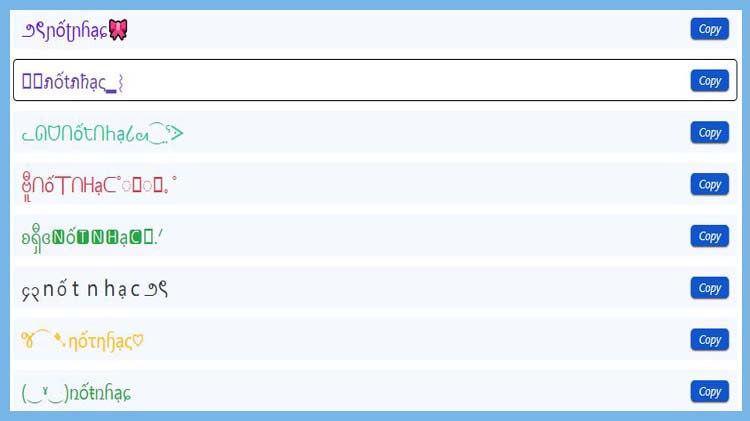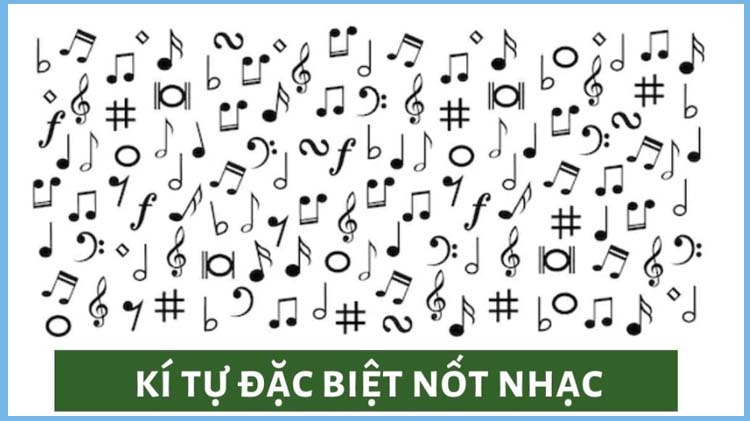
Tuyển tập các kí tự nốt nhạc đơn sắc, có màu sắc, chữ nghệ thuật 2025
Kí tự nốt nhạc hay kí tự âm nhạc là một trong những biểu tượng được sử dụng phổ biến trong những status trên facebook, instagram, tiktok hay được dùng để đặt tên người chơi trong các tựa game phổ biến như FF, Liên Quân, PUBG,... Những kí tự này không chỉ gây ấn tượng với người đọc mà còn thể hiện khả năng sáng tạo và niềm đam mê âm nhạc của người sử dụng.
Trong bài viết này của MobiFonts, các kí tự đặc biệt nốt nhạc được phân loại thành 3 nhóm chính là kí tự nốt nhạc đơn sắc, kí tự nốt nhạc có màu sắc và kí tự âm nhạc chữ nghệ thuật. Ngoài ra, chúng tôi cũng giải đáp những thắc mắc của người đọc về các kí tự đặc biệt âm nhạc này.
Kí tự nốt nhạc đặc biệt là một thuật ngữ chung để chỉ các biểu tượng, ký hiệu và emoji được sử dụng để biểu thị các yếu tố liên quan đến âm nhạc, đặc biệt là các nốt nhạc trên khuông nhạc.
Kí tự nốt nhạc đơn sắc là các ký hiệu nốt nhạc cơ bản hơn, thường không có màu sắc và chủ yếu thuộc khối ký tự Miscellaneous Symbols (U+2600–U+26FF) trong Unicode. Là các kí tự nốt nhạc và hóa biểu cơ bản, phổ biến như ♩, ♪, ♫, ♬, ♭, ♮, ♯, có thể được sử dụng để trang trí hoặc trong các văn bản.
Sau đây là bảng tổng hợp các kí tự nốt nhạc đơn sắc nổi bật được sử dụng phổ biến nhất hiện nay:
Kí Tự |
Mã Unicode |
Tên Unicode Chính Thức |
Mô Tả Ngắn |
♩ |
U+2669 |
Quarter Note |
Nốt đen (nốt một phách). |
♪ |
U+266A |
Eighth Note |
Nốt móc đơn (nửa phách). |
♫ |
U+266B |
Beamed Eighth Notes |
Hai nốt móc đơn nối đuôi. |
♬ |
U+266C |
Beamed Sixteenth Notes |
Hai nốt móc kép nối đuôi. |
♭ |
U+266D |
Music Flat Sign |
Dấu Giáng (làm nốt nhạc thấp xuống nửa cung). |
♮ |
U+266E |
Music Natural Sign |
Dấu Hoàn/Bình (hủy bỏ dấu thăng/giáng). |
♯ |
U+266F |
Music Sharp Sign |
Dấu Thăng (làm nốt nhạc cao lên nửa cung). |
𝄞 |
U+1D11E |
Musical Symbol G Clef |
Khóa Sol. |
𝄢 |
U+1D122 |
Musical Symbol F Clef |
Khóa Fa. |
𝄡 |
U+1D121 |
Musical Symbol C Clef |
Khóa Đô. |
𝄪 |
U+1D12A |
Musical Symbol Double Sharp |
Dấu Thăng Kép (cao lên một cung). |
𝄫 |
U+1D12B |
Musical Symbol Double Flat |
Dấu Giáng Kép (thấp xuống một cung). |
♩﹒ |
U+2669 U+FE0E |
Quarter Note With Dot (Text Style) |
Nốt đen chấm dôi (thêm dấu chấm sau). |
♪﹒ |
U+266A U+FE0E |
Eighth Note With Dot (Text Style) |
Nốt móc đơn chấm dôi. |
𝅝 |
U+1D15D |
Musical Symbol Whole Note |
Nốt tròn (nốt bốn phách). |
𝅗𝅥 |
U+1D15E |
Musical Symbol Half Note |
Nốt trắng (nốt hai phách). |
𝅘𝅥 |
U+1D15F |
Musical Symbol Quarter Note Stem Up |
Nốt đen có đuôi hướng lên. |
𝅘𝅥𝅮 |
U+1D160 |
Musical Symbol Eighth Note Stem Up |
Nốt móc đơn có đuôi hướng lên. |
𝅘𝅥𝅯 |
U+1D161 |
Musical Symbol Sixteenth Note Stem Up |
Nốt móc kép có đuôi hướng lên. |
𝄐 |
U+1D110 |
Musical Symbol Fermata |
Dấu mắt ngỗng (ngân dài nốt nhạc). |
𝄑 |
U+1D111 |
Musical Symbol Fermata Below |
Dấu mắt ngỗng đặt dưới nốt nhạc. |
Bên cạnh các kí tự đơn sắc thì kí tự âm nhạc đặc biệt có màu sắc ( hay còn gọi là emoji nốt nhạc, icon nốt nhạc) như 🎵, 🎶, 🎼 cũng là sự lựa chọn thú vị để tạo điểm nhấn cho thông điệp mà bạn muốn truyền tải.
Đây là những hình ảnh đồ họa nhỏ, có màu sắc (hoặc đen trắng tùy theo thiết kế của từng nền tảng). Các kí tự này đã được chuẩn hóa trong Unicode và thuộc khối kí tự Miscellaneous Symbols and Pictographs (U+1F300–U+1F5FF).
Dưới đây là danh sách các ký tự âm nhạc đặc biệt có màu sắc mà bạn không thể bỏ qua:
Kí Tự |
Mã Unicode |
Tên Unicode Chính Thức |
Mô Tả Ngắn |
🎵 |
U+1F3B5 |
Musical Note |
Nốt móc đơn. Biểu thị âm nhạc nói chung, một bài hát, giai điệu. |
🎶 |
U+1F3B6 |
Multiple Musical Notes / Musical Notes |
Chùm 3 nốt móc đơn. Biểu thị nhiều bài hát, playlist, không khí âm nhạc. |
🎼 |
U+1F3BC |
Musical Score |
Một đoạn khuông nhạc với các nốt. Biểu thị bản nhạc, tác phẩm âm nhạc. |
Để thể hiện đam mê âm nhạc một cách đặc biệt và tinh tế không chỉ dừng lại ở các biểu tượng nốt nhạc mà bạn hoàn toàn có thể sử dụng các kí tự âm nhạc chữ nghệ thuật. Những cách kết hợp này được sử dụng trong các bài đăng để biểu lộ cảm xúc, hay đơn giản chỉ để trang trí và làm đẹp bài viết của bạn. Bạn có thể dễ dàng tìm thấy kí tự đặc biệt âm nhạc trên các công cụ tạo kí tự trực tuyến hoặc thông qua ứng dụng MobiFonts.
꧁༒âɰ•ɳɧạͼ༒꧂
âɱɲħạɔⱭ͞ ̶͞ ̶͞ ̶͞ لں͞
(‿ˠ‿)âɷռɦạɕ
જ⁀➴âɱηɧạς♡
၄၃âmnhạc౨ৎ
ᓚᘏᗢâɱՈҺạ८ᘛ⁐̤ᕐᐷ
౨ৎâɱɲɦạɕ🎀
ദ്ദി ˉ͈̀꒳ˉ͈́ )✧âണղհạç
(๑﹏๑//)âℳทɦạ☪
Âɯnɥạɔ☃︎\
♰âM̆♰N̆H̆ạC̆♰
Ϟâṃϟṅһạċ⚡︎
亗âɱn♄ạ☾ෆ
㊝âMムNHạC모
—̳͟͞͞♥âლղɦạℭ
´꒳`âⓂⓃⒽạⒸ×͜×
ミ★âмɴнạc★彡
Nếu vẫn gặp phải những thắc mắc về các kí tự hình nốt nhạc, bạn có thể tham khảo nội dung giải đáp câu hỏi thường gặp về các kí tự này dưới đây!